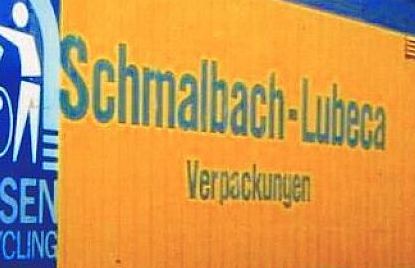
Ich suche die Schrifttype auf einem Firmenfahrzeug
ich suche die Schrifttype, mit der die Firmenbeschriftung auf den Lastwagen des Unternehmens erstellt wurde. Der Ausschnitt zeigt einen LKW von vor 40 Jahren; die Firma gibt es schon lange nicht mehr.
Sieht nach einer "Helvetica Compressed" aus.
Ich vermute die Helvetica Compressed ist es nicht (siehe z.B. r). Eher noch die Condensed Bold – aber das S? Ich habe aber momentan auch noch keine Entsprechung finden können. Weder bei der AG noch bei der Nimbus war auf die Schnelle etwas wirklich Passendes zu finden. Vielleicht hat man auch eine gestaucht?
Hallo Robert,
ich habe mir nun einmal die verschiedenen Schriften angesehen und verglichen. Bei der Compressed sind die Strichstärken zu dick, gerade beim großen "S" bleibt zu wenig Platz zwischen der Schräge und den Enden links unten/rechts oben; dafür sind die Abstände zwischen den Buchstaben schmal genug. Bei der Condensed Bold wirkt die Strichstärke passender, aber die Buchstaben stehen zu weit auseinander. Irgendwie habe ich den Eindruck, als ob die Schrift leicht "in die Höhe gezogen" worden wäre; und vielleicht hat man auch die Abstände "angepaßt". Leider habe ich kein anderes Foto, und die Ansicht ist ja auch durch den Betrachtungswinkel verzerrt.